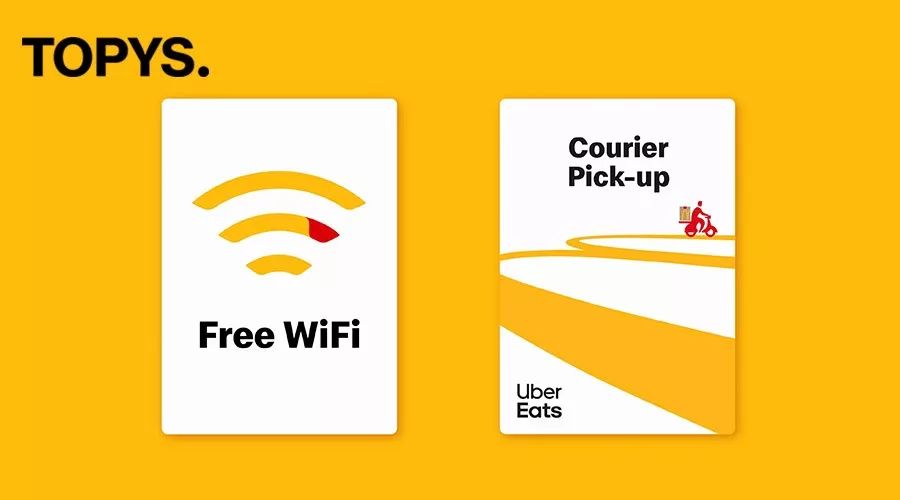
你们熟悉的“金拱门”悄悄单飞啦
如果你有留心观察麦当劳最近的一些动作,或许能窥出一些端倪。
这个快餐界的巨头正在悄咪咪地进行一项全新的品牌重塑活动,重新设计下,它最引人注目的标志是——金色拱门和品牌英文名"McDonald's"无需再紧紧捆绑,拱门可以以更活跃、更有趣的形式跳脱出来,独自美丽。
对于老麦早期的忠实粉丝来说,麦当劳这个名字可能会让他们立马联想到一些奇特的形象:金色的拱门、巨无霸、盛着薯条的红色包装盒、麦当劳叔叔(Ronald McDonald)。但就在最近两年,如果你有留意老麦在世界各地的广告,你会发现它被玩脱儿了:信息愈发复杂,字体就像大杂烩,而色彩体系好像是直接从彩虹中提取出的。
去年,麦当劳就发现了这些问题,开始着手对其全球视觉形象重新梳理。听起来并非容易事儿,作为一个全球连锁餐饮品牌,麦当劳的规模实在太庞大:全球120个国家约有3.5万家餐厅,仅美国就有1.7万家。麦当劳副总裁兼全球品牌总监科林·米切尔(Colin Mitchell)表示,该公司的使命是将麦当劳打造成一家“更现代、更进步的汉堡公司”。
为了变得让它显得更具现代感,米切尔的团队与首席营销官西尔维亚·拉格纳多(Silvia Lagnado)一起深入挖掘品牌的历史。
其中的一个灵感来自麦当劳1971年发起的一项具有开创性的活动“你今天应该休息一下”(You deserve a break today),主张消费者与品牌之间的有趣互动。2017年末,麦当劳聘请Turner Duckworth工作室领导品牌升级工作。设计总监泰勒·布鲁克斯(Tyler Brooks)表示:“这是为了化繁为简,我们想回归最基本的东西。”
改造的思路围绕——“这能给人们带来快乐吗?这是一件让人感觉快乐的事情吗?如果是,就留下,如果不是,就把它处理掉了。”
麦当劳的金色拱门在这次改造中被推至了舞台中心,根据新的设计规则,标志性的拱门可以独立展示。在此之前,他们一直与“McDonald's”这个单词连在一起。
麦当劳也允许其不同的国际市场在拱门上挖掘出一些更有创意的玩法。因为拱门有着惊人的图形属性,有弹性的创作空间,看起来也极具能量。它甚至都不必全部完整呈现,在广告中可以被裁剪或调整,以助实现不同的想法。
△在这组标志中,拱门的作用是双重的,它传达了一种关于“传递”的概念。
这一波品牌形象更新中,还有一些明显的变化。
关于调色板的层次结构
历史上,麦当劳一直是一个以红色为主、黄色为点缀的品牌。而经过这轮大的形象调整,拱门的金黄色现在占据了视觉的中心,配以红色,就像上图中由Landini & Associates设计的时代广场旗舰店的内景一样。
“品牌中太多的红色让人感觉咄咄逼人、吵吵嚷嚷。”同时,红色已经成为快餐类餐厅的默认颜色,选择黄色也能从中加以区别。“当你看到阳光下的黄色时,你会忍不住感到高兴。”
关于字体
麦当劳目前在市场上只采用一种字体Speedee,共分三种粗细。即使在字体上,拱门也起到了启发作用,从符号的形状和曲线中提取字形和字符的比例。
关于Patterns 和 icons
麦当劳在视觉识别系统中采用了“flawesome”的原则,保留食物中自然和不规则的状态。“薯条杂乱无序,面包的摆放也不规则,奶酪的融化也是如此。这对麦当劳来说非常新鲜,也非常人性化和真实。”
△麦当劳全球大会上销售的周边产品
简单总结起来,麦当劳为了让自己看起来更现代,拱门“单飞”之后,变得更独立、自由了,整体风格上,不再强调一种模式化的有序,而是一种追求真实的美感。你可以把这次改变想象成一个梳着齐刘海戴着圆框眼镜的好好学生,开始甩开那些不必要的束缚,走起了独立、率性的风格。
想想那些时尚icon们,或许麦当劳的这一次改变,也在引领着下一股风潮的来临。